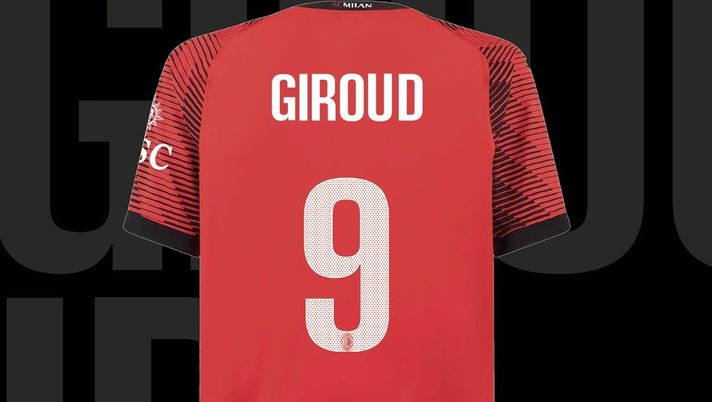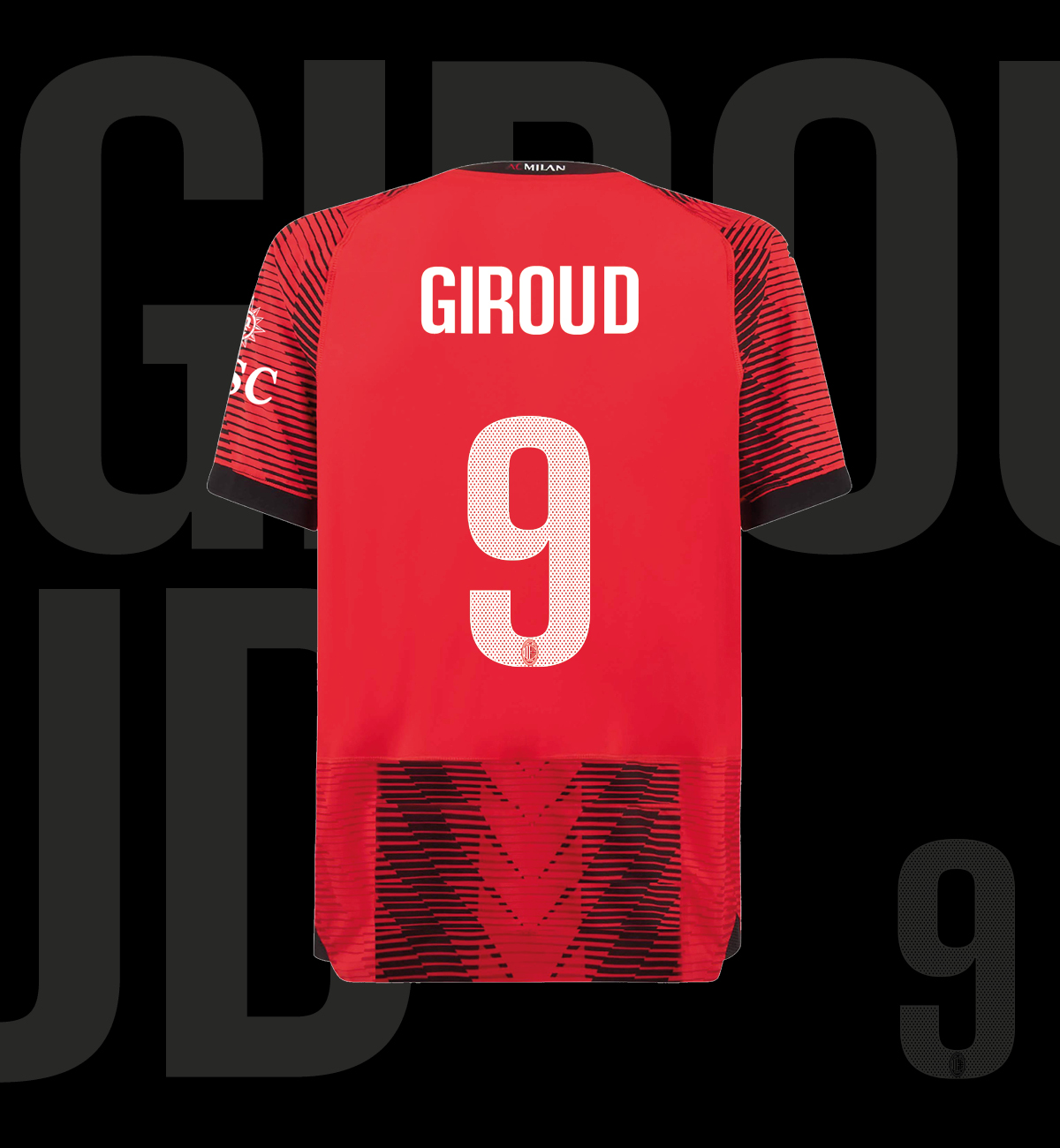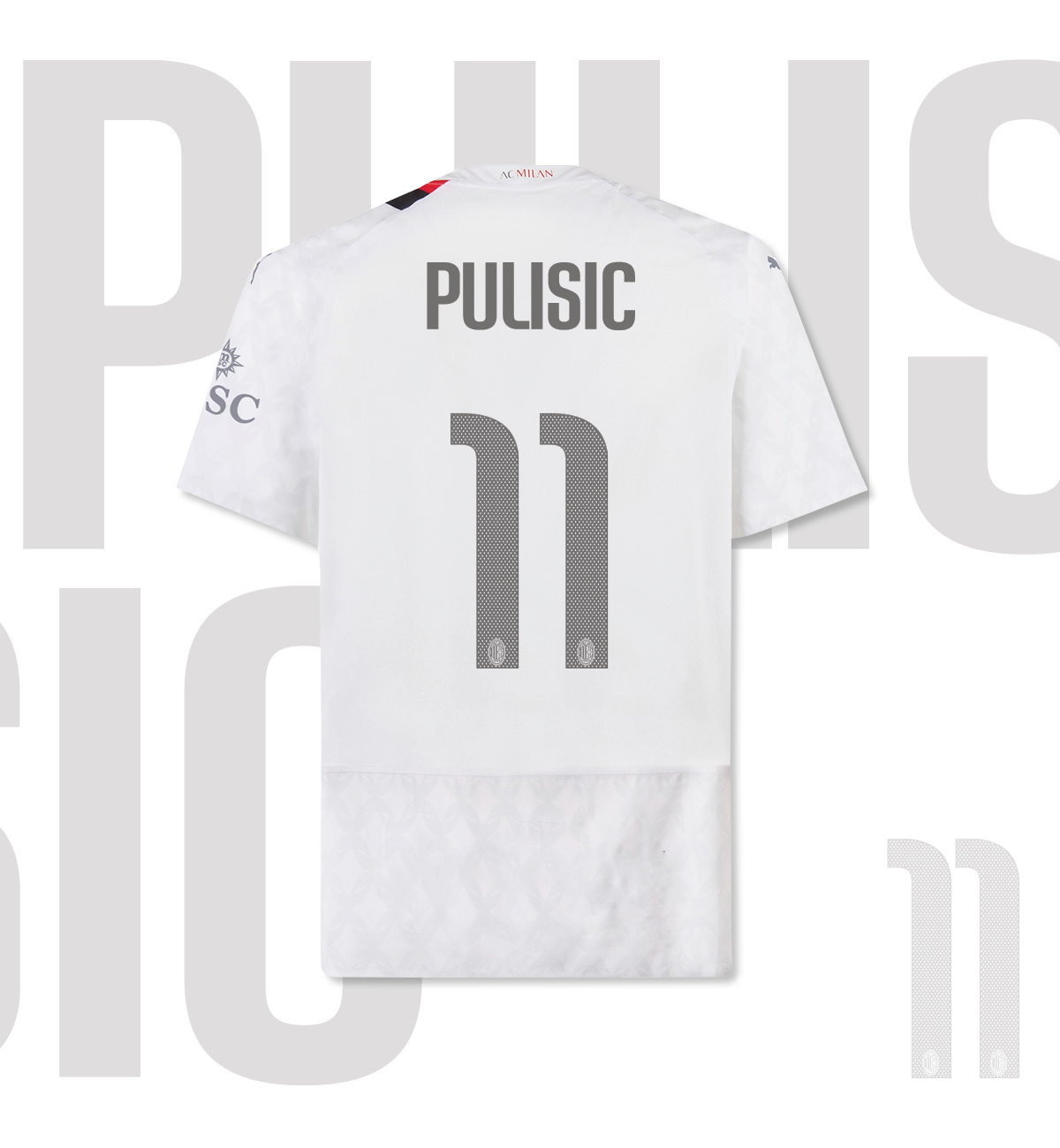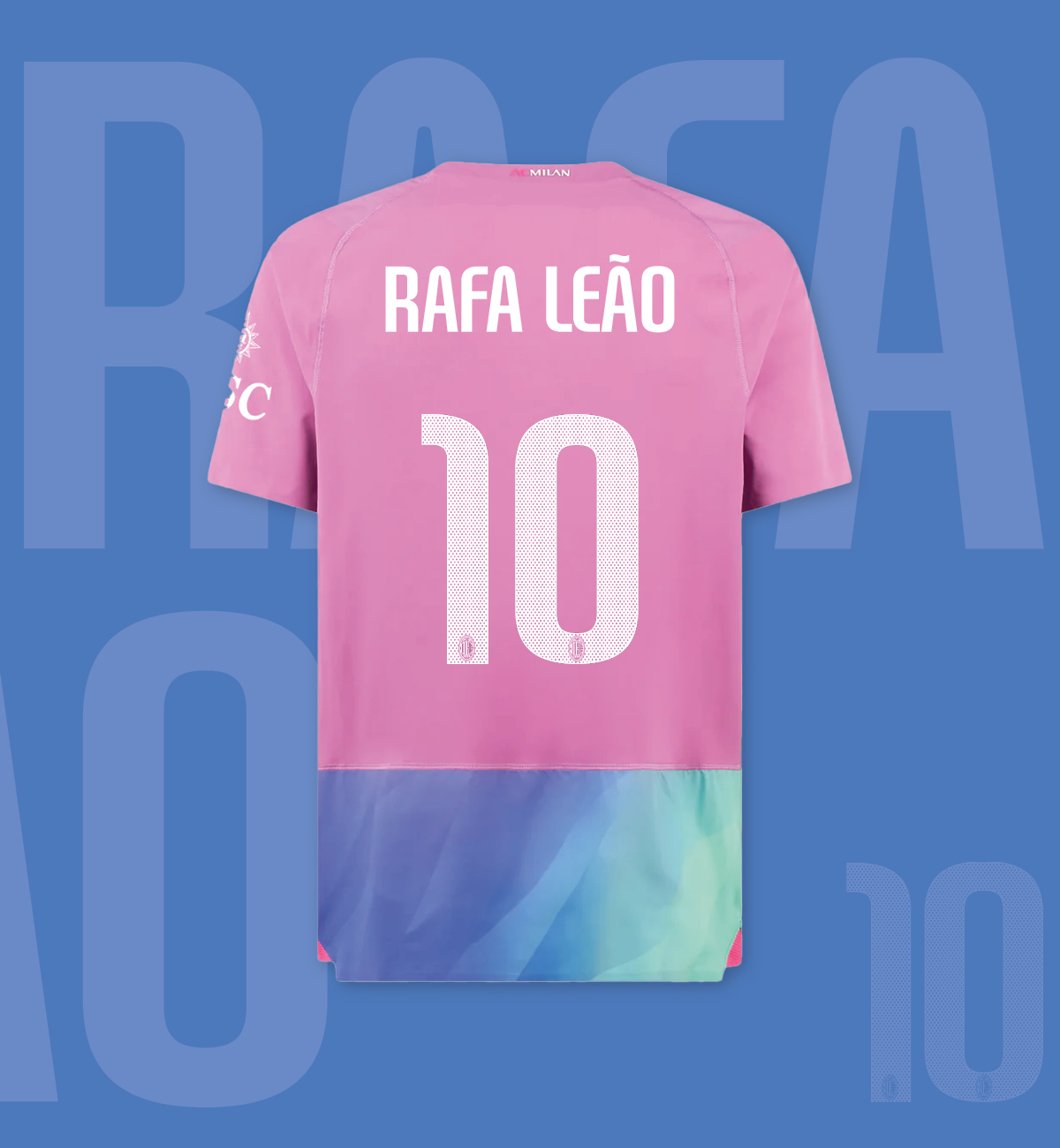
AC Milan adotta per la prima volta un font dedicato a una singola competizione sull’intero matchwear stagionale – che si tratti di maglie Home, Away o Third. A partire dal 2020/21, la Lega Serie A ha infatti introdotto un carattere standard per le maglie dei calciatori e, da quel momento, tutti i club italiani hanno iniziato ad utilizzarlo anche in tutte le competizioni europee.